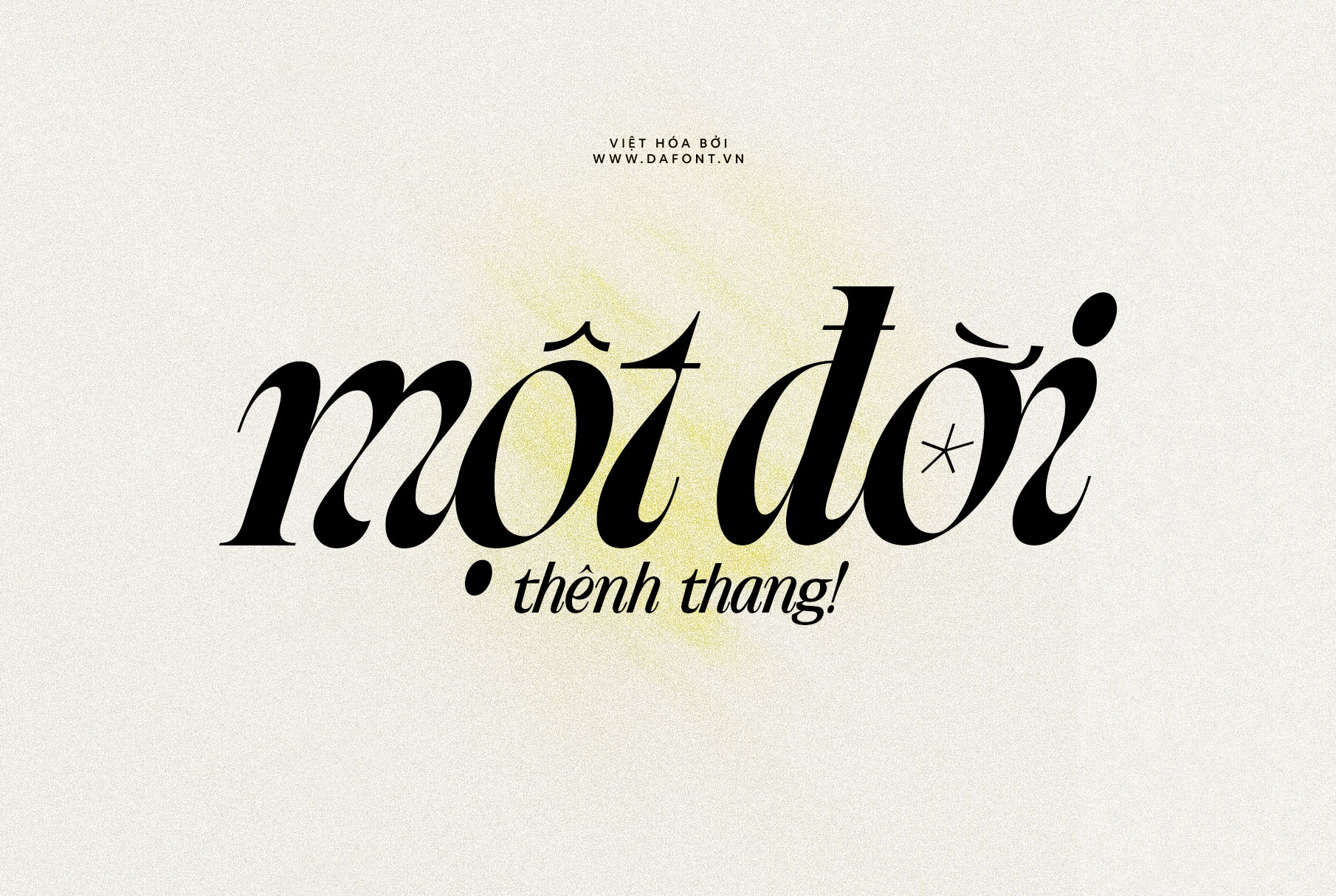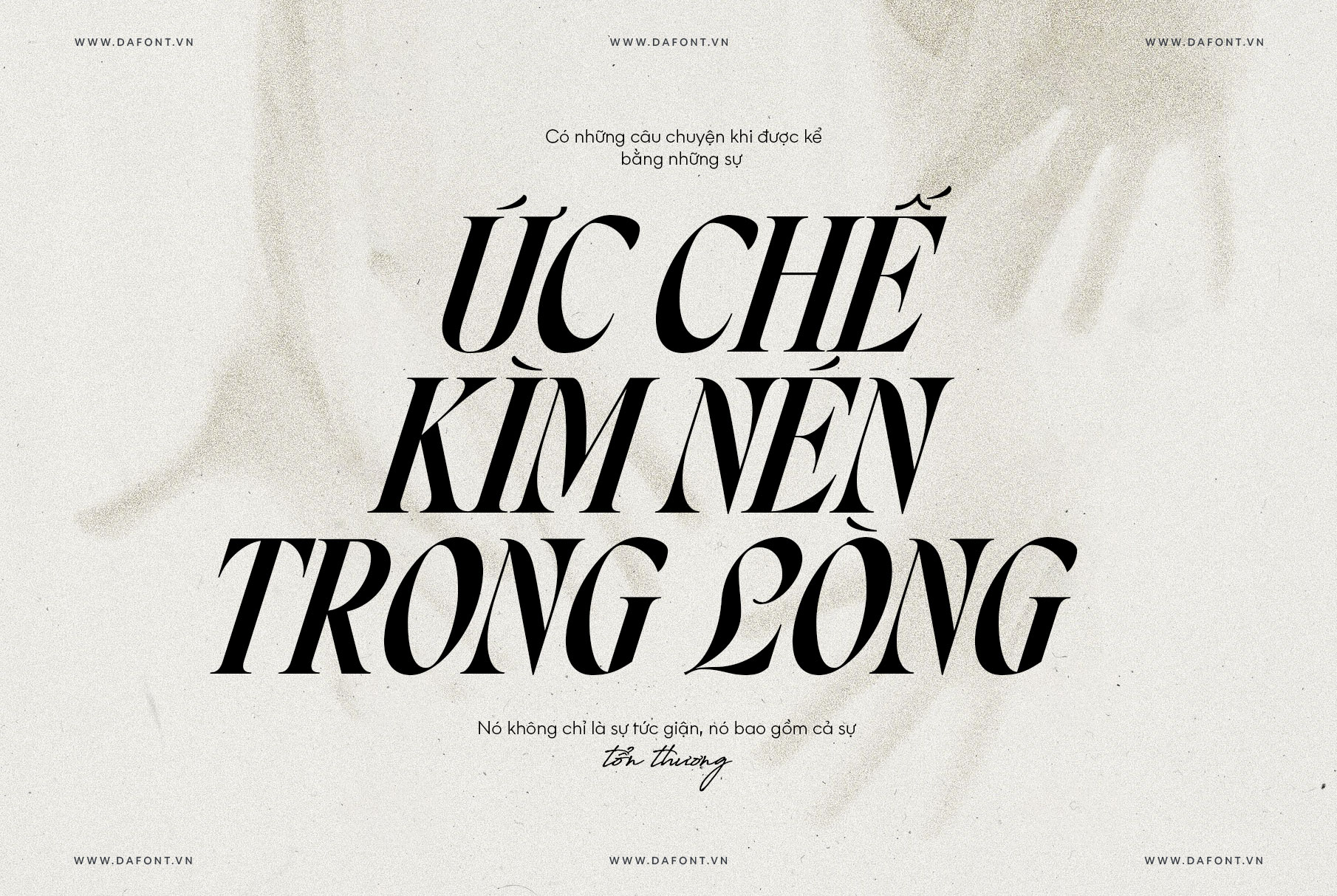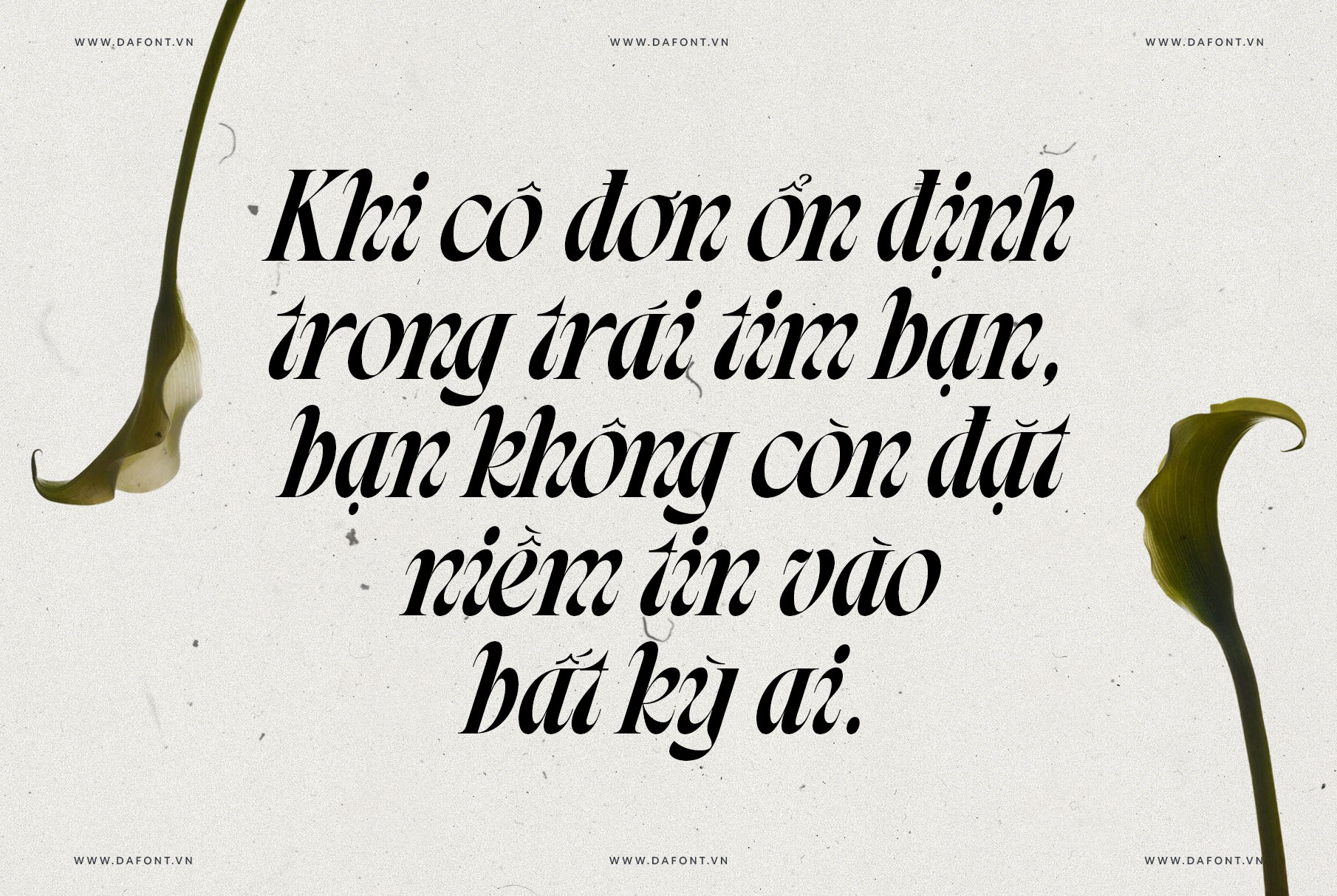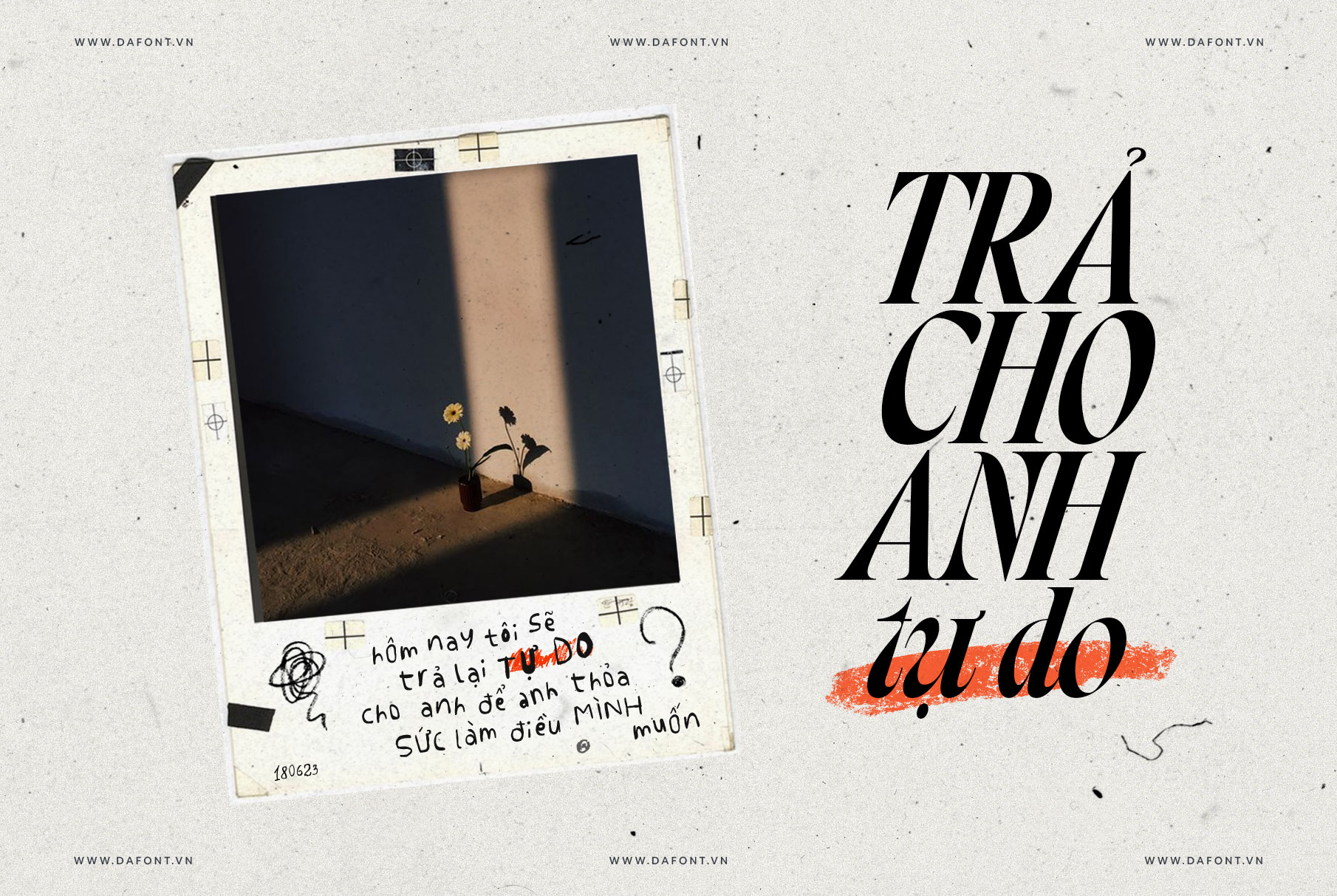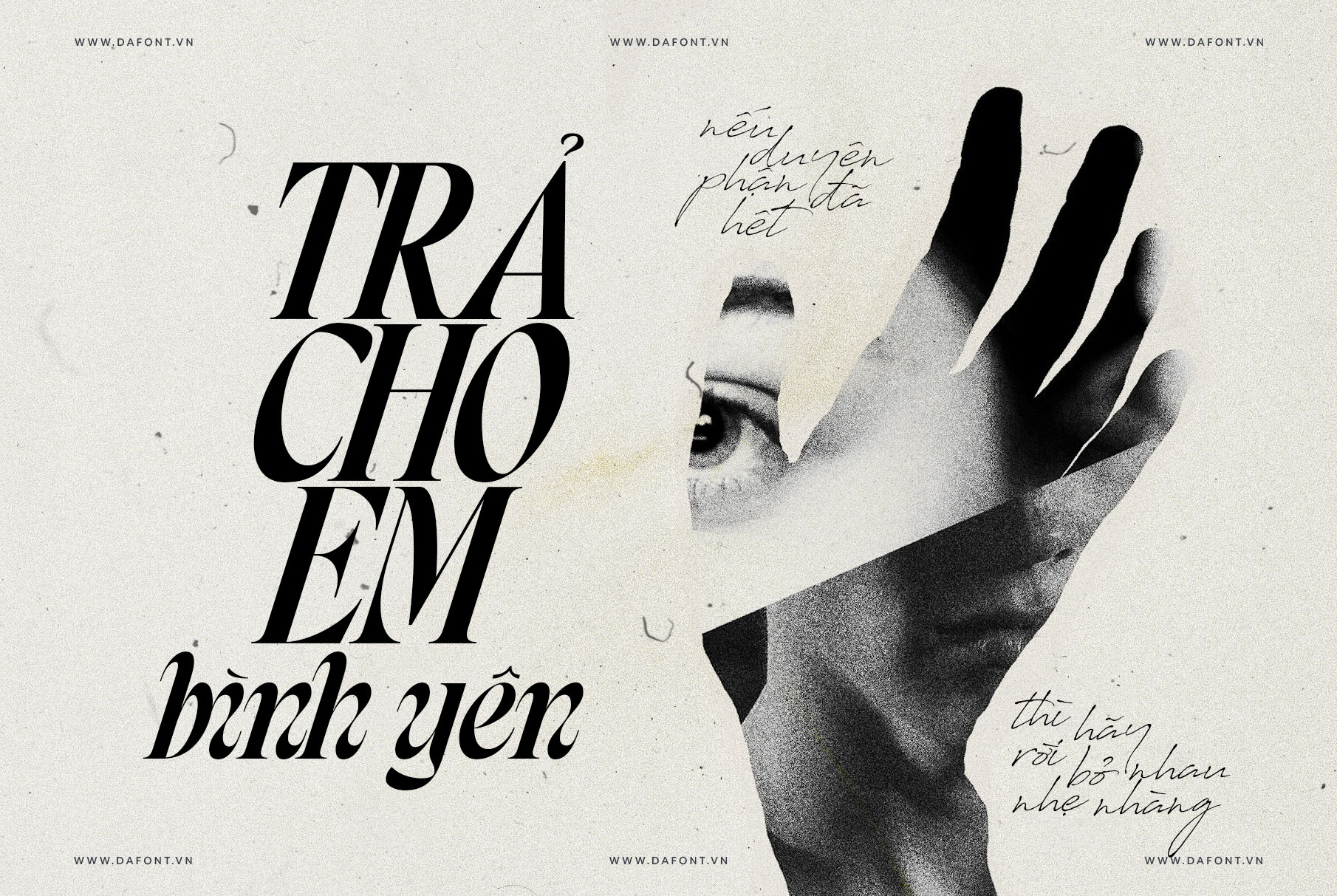
Trong thế giới thiết kế đầy sáng tạo, việc chọn một font chữ phù hợp có thể làm nổi bật toàn bộ dự án của bạn. DFVN TAN – SOMETIMES font là một sự lựa chọn hoàn hảo, mang đến phong cách retro độc đáo, vừa nổi bật vừa cuốn hút. Font chữ này sẽ là “vũ khí bí mật” giúp bạn chinh phục bất kỳ dự án thiết kế nào.
TAN – SOMETIMES là một lựa chọn đa năng, phù hợp với nhiều lĩnh vực thiết kế nhờ phong cách retro nổi bật và khả năng tạo điểm nhấn ấn tượng có thể sử dụng cho poster, bìa sách, tạp chí, bìa album, thiệp mời, nội dung trên mạng xã hội…
Đặc điểm nổi bật của DFVN TAN – SOMETIMES
1. Phong cách retro đậm chất nghệ thuật
TAN – SOMETIMES không chỉ là một font chữ thông thường, mà còn là một biểu tượng của sự sáng tạo. Với thiết kế chữ nghiêng đậm (italic bold), font chữ này gợi nhớ đến những năm tháng hoài cổ đầy cảm xúc, mang lại cảm giác thân thuộc và đầy tính nghệ thuật.
2. Tính ứng dụng đa dạng
Dù bạn đang làm poster, thiết kế bìa album, hay sáng tạo nội dung cho mạng xã hội, TAN – SOMETIMES đều phù hợp. Font chữ này đặc biệt lý tưởng cho các dự án mang phong cách trẻ trung hoặc cần tạo điểm nhấn mạnh mẽ.
3. Làm nổi bật thiết kế
Sự kết hợp giữa các đường nét có chút cứng cáp và tỷ lệ cân đối giúp TAN – SOMETIMES dễ dàng nổi bật trong mọi bố cục. Đây chính là lựa chọn hoàn hảo để thu hút ánh nhìn và truyền tải thông điệp của bạn một cách hiệu quả.
4. Bắt kịp xu hướng thiết kế hiện đại
Phong cách retro đang quay trở lại mạnh mẽ trong các lĩnh vực thiết kế và DFVN TAN – SOMETIMES chính là đại diện tiêu biểu cho xu hướng này. Việc sử dụng font chữ này không chỉ giúp thiết kế của bạn trở nên thời thượng mà còn khẳng định gu thẩm mỹ tinh tế.
DFVN TAN – SOMETIMES: Phong Cách retro nổi bật cho thiết kế hiện đại
DFVN TAN – SOMETIMES không chỉ là một công cụ thiết kế mà còn là một biểu tượng của phong cách và sự sáng tạo. Nếu bạn muốn mang lại hơi thở hoài cổ nhưng vẫn mang đậm nét hiện đại, sự táo bạo và cuốn hút cho dự án của mình, hãy thử ngay font chữ này!
Font chữ được Việt hóa cẩn thận, các dấu cũng được chỉnh sửa lại đôi chút để phù hợp hơn với font. Ngoài ra, kering lại hoàn toàn để khoảng cách của các ký tự tối ưu hơn.